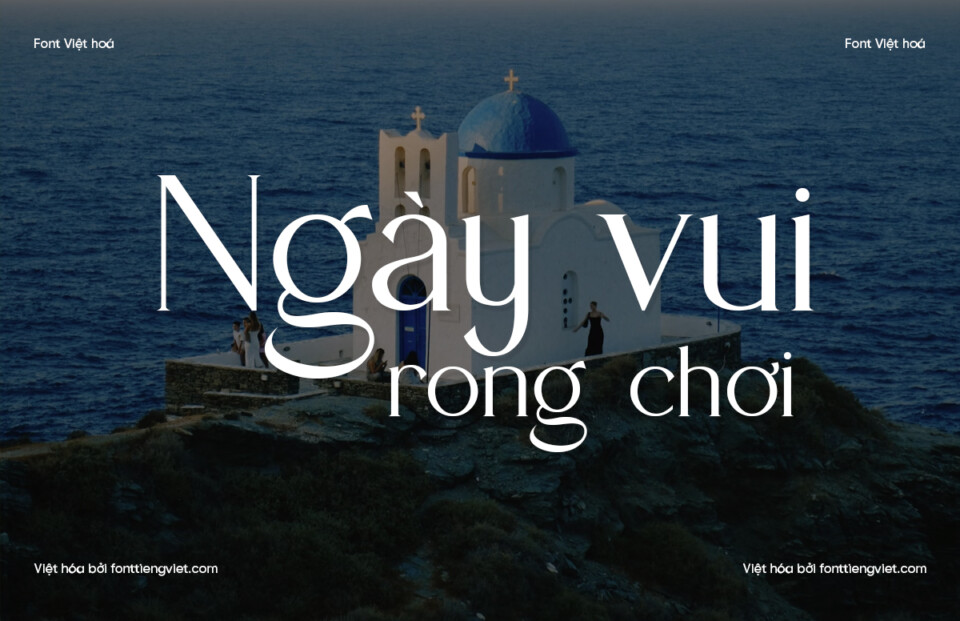
Font Việt hóa 1FTV VIP Vocago
Font Việt hóa 1FTV VIP Vocago – Bộ font chữ thiết kế sang trọng và hiện đại miễn phí
Giới thiệu về Font Việt hóa 1FTV VIP Vocago trong thiết kế đồ họa
Trong thế giới sáng tạo ngày nay, việc lựa chọn một bộ Font Miễn Phí chất lượng đóng vai trò then chốt giúp tác phẩm của bạn trở nên nổi bật và chuyên nghiệp hơn. Font Việt hóa 1FTV VIP Vocago là một trong những lựa chọn hàng đầu được cộng đồng designer yêu thích nhờ sự kết hợp hoàn hảo giữa nét hiện đại và sự tinh tế trong từng đường cong của ký tự. Được tinh chỉnh kỹ lưỡng để phù hợp với bảng mã tiếng Việt, bộ font này loại bỏ hoàn toàn các lỗi hiển thị dấu phổ biến, giúp người dùng tự tin thể hiện ý tưởng trên mọi nền tảng số. Đối với các bạn học sinh hay thầy cô giáo, việc sử dụng bộ chữ này vào các bài giảng hay báo cáo sẽ giúp nội dung trở nên dễ đọc và thu hút thị giác một cách tự nhiên nhất.
Những đặc điểm nổi bật của bộ Font Việt hóa 1FTV VIP Vocago
Thiết kế thanh lịch và tính ứng dụng cao
Font Việt hóa 1FTV VIP Vocago mang trong mình phong cách thiết kế tối giản nhưng không kém phần sang trọng. Các nét chữ được bo tròn mềm mại kết hợp với độ dày vừa phải, tạo ra cảm giác cân đối và hài hòa cho tổng thể văn bản. Đây là công cụ đắc lực cho việc thiết kế logo, tiêu đề tạp chí, bìa sách hoặc các ấn phẩm truyền thông sự kiện tại trường học. Khả năng hiển thị sắc nét của font giúp người xem không bị mỏi mắt, đồng thời tạo ra một không gian nghệ thuật đầy cảm hứng cho người sử dụng.
Khả năng tương thích và tối ưu hóa tiếng Việt
Điểm mạnh lớn nhất của Font Việt hóa 1FTV VIP Vocago chính là quy trình Việt hóa chỉn chu. Từng dấu thanh như huyền, sắc, hỏi, ngã, nặng được đặt ở vị trí chuẩn xác, không bị đè nét hay quá cao so với ký tự chính. Điều này đặc biệt quan trọng khi bạn in ấn các tài liệu học tập hoặc làm Slide thuyết trình. Sự đồng nhất trong bộ mã giúp font vận hành mượt mà trên các phần mềm thiết kế phổ biến như Adobe Photoshop, Illustrator hay thậm chí là các ứng dụng văn phòng cơ bản như Microsoft Word và PowerPoint.
Để tận dụng tối đa vẻ đẹp của Font Việt hóa 1FTV VIP Vocago, bạn nên ưu tiên sử dụng bộ font này cho các tiêu đề lớn hoặc các đoạn trích dẫn quan trọng. Hãy kết hợp nó với một font chữ không chân (sans-serif) đơn giản ở phần nội dung để tạo sự tương phản chuyên nghiệp. Trong môi trường giáo dục, giáo viên có thể dùng font này để trang trí bảng tin hoặc làm thiệp chúc mừng, giúp khơi gợi sự sáng tạo cho học sinh. Lưu ý rằng việc cài đặt font rất đơn giản, bạn chỉ cần tải về, giải nén và thực hiện thao tác cài đặt trực tiếp vào hệ thống máy tính là có thể sử dụng ngay lập tức cho mọi dự án của mình.
Tổng kết về giá trị của bộ Font Việt hóa 1FTV VIP Vocago